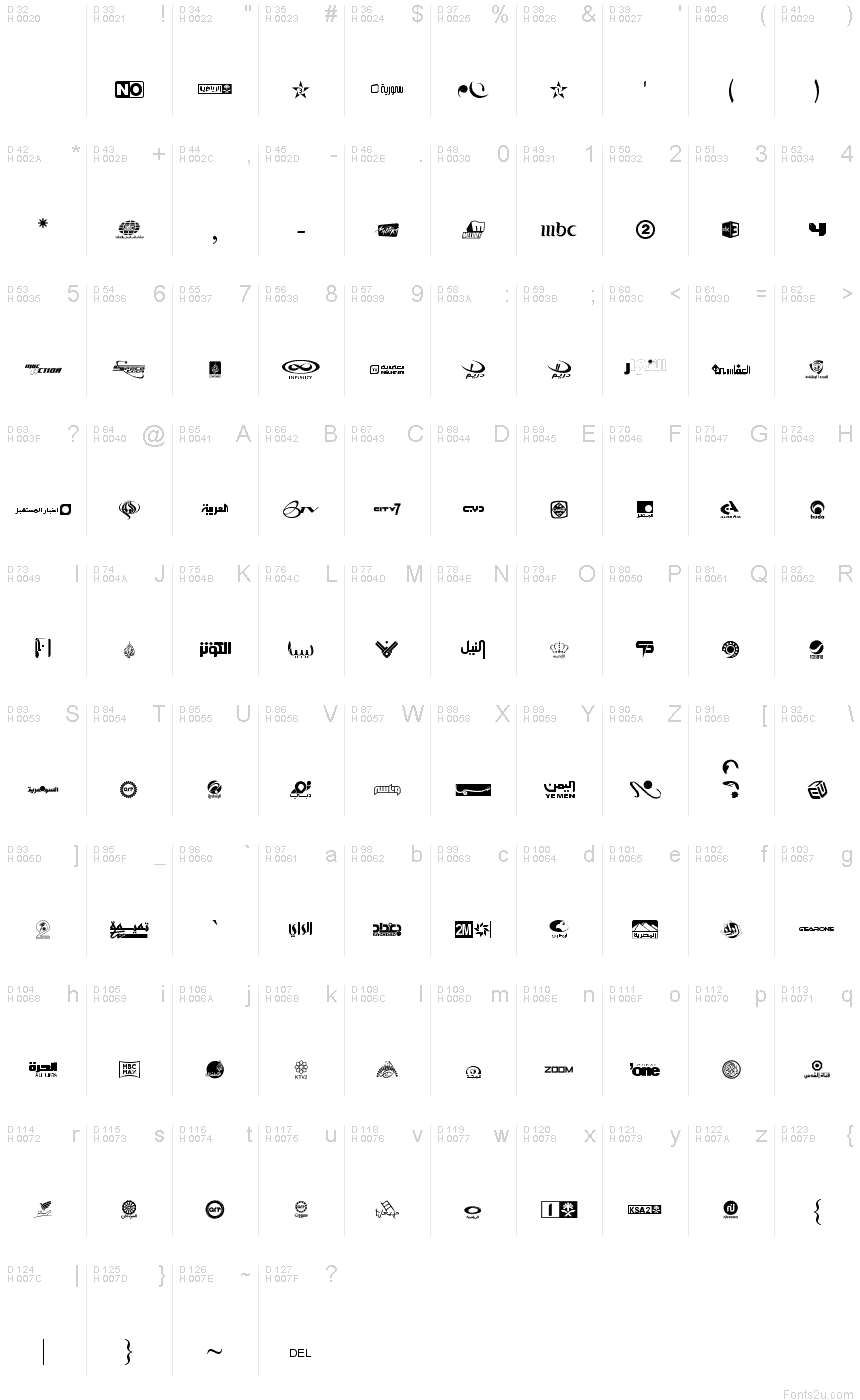
Arab TV Logos od Mustaphy Asbbara je bezplatný font typu dingbat tvořený logy a emblémy arabských televizních stanic. Výrazná arabská písmena se zde potkávají s geometrickými znaky, zářivými pečetěmi a plynulými křivkami typickými pro televizní vysílání, což kolekci dodává nádech kompaktního archivu regionálních médií.
Jako bezplatný font se skvěle hodí na plakáty o historii médií, televizní editorialy, přehledy kanálů, archivní výstavy nebo tematické moodboardy. Kompaktní tvary log využijete i u úvodních titulků a krátkých nadpisů, kde jejich hustá sazba a emblémové siluety udrží kompozici i bez dalších ozdob.
Arab TV Logos Font
Výběr nejoblíbenějších log arabských televizních kanálů